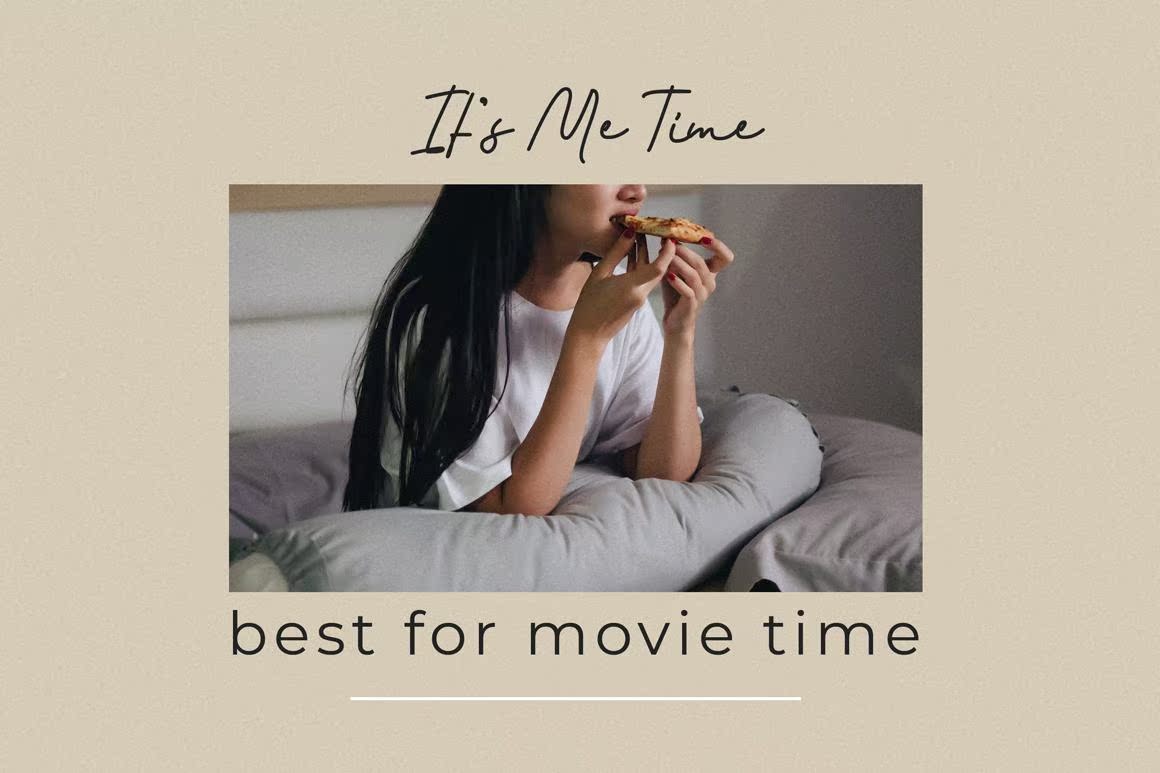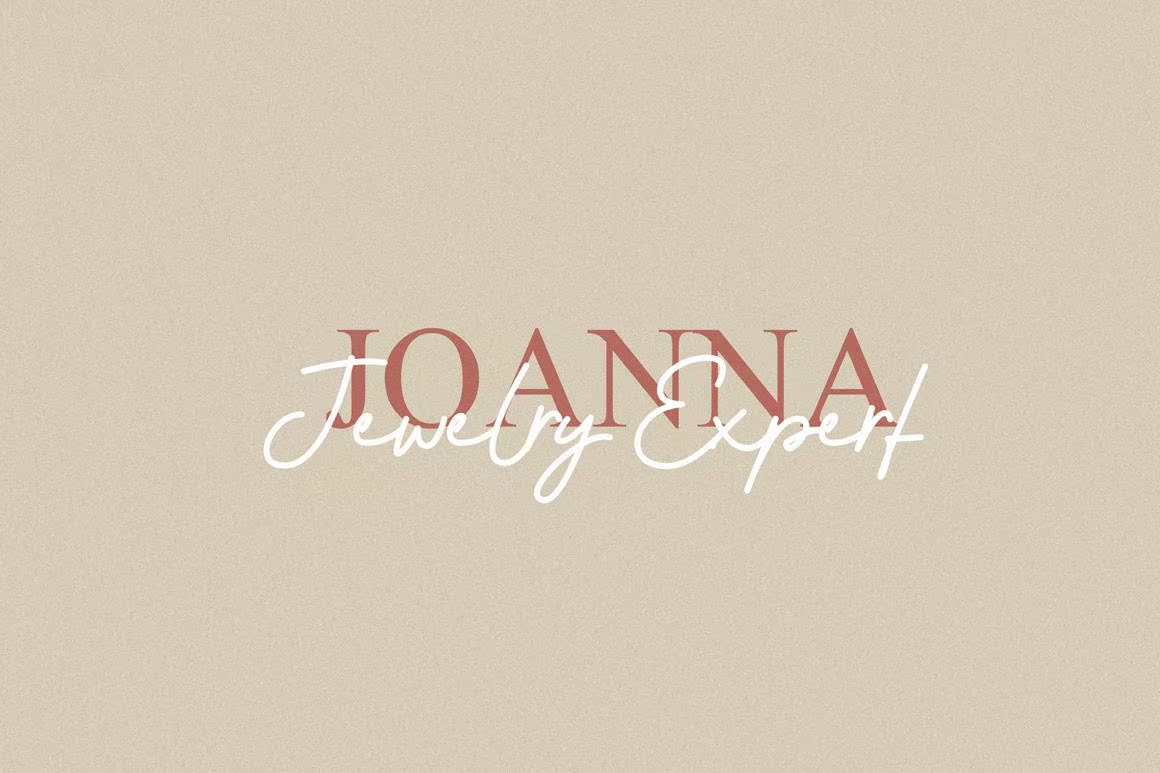
您好,BrittleyMonolineScriptFontIsStylishFontIsylishFonts与ModernStylishFonts共同制作您的项目,如Elogos,WeddingVitations,branding,signage,labels,signature,Bookcover,海报,Quotes Looks Beautifula and Leganthello,BrittleyMonolineScriptFontIsylishFonts与ModernStylishFonts共同制作您的项目,书皮、海报、引文